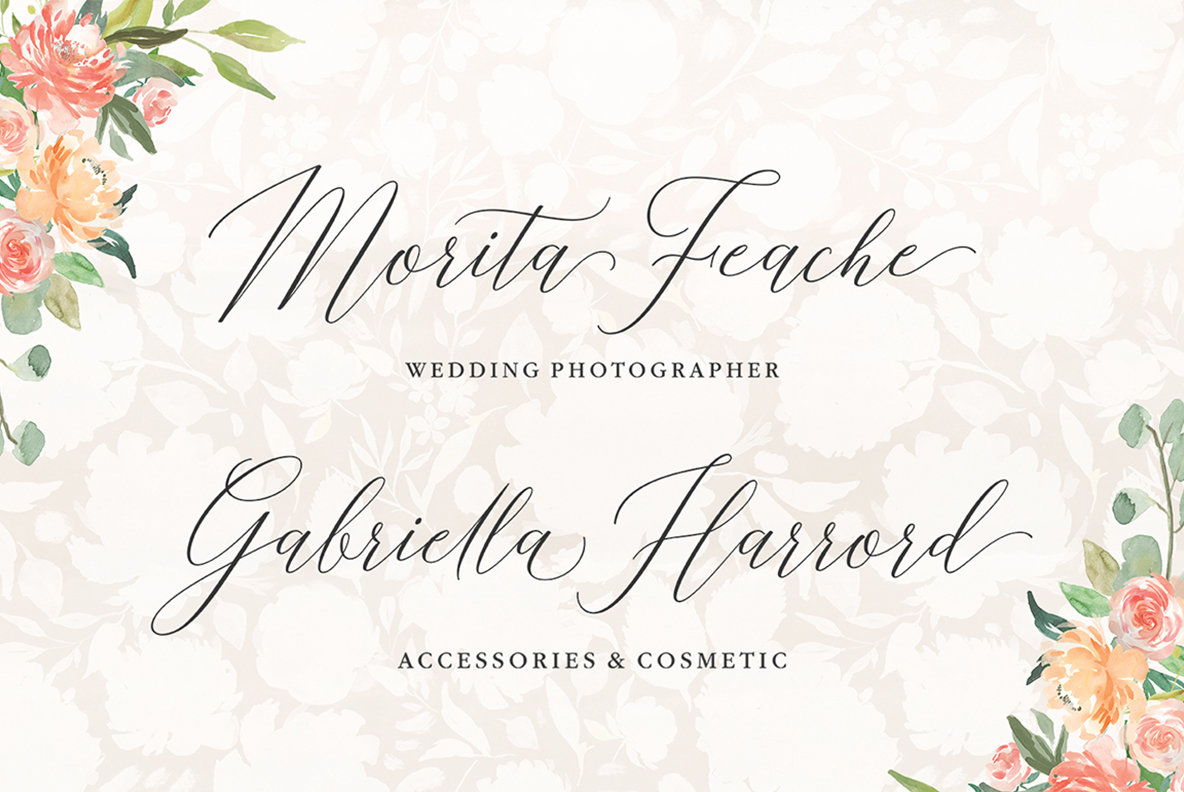
Каллиграфические свадебные логотипы
Лучше всего передать самое сокровенное поможет персональный дизайн ручной работы.
Не случайно кастомная каллиграфия и надписи от руки признаны классикой свадебного дизайна.
Одна из сфер, где каллиграфия работает наиболее хорошо, — различные производства ручной работы, например, создание тортов. Если вы хотите добавить уникальный штрих, подчеркнуть личную преданность или вы владеете бизнесом по производству свадебных продуктов, подумайте об использовании каллиграфии в своем лого.
Создайте свадебный логотип, в который вы влюбитесь
Неважно, планируете ли вы собственную свадьбу или владеете бизнесом, связанным со свадьбами, — правильный логотип может точно передать ваш стиль. Поэтому убедитесь, что вы выбрали именно тот логотип, который лучше всего подходит именно вам. А создать свадебный лендинг, если перед вами стоит такая задача, вам поможет конструктор от LPgenerator.
50 лучших свадебных шрифтов: стиль вашей свадебной открытки 2023
Вы ищете лучшие свадебные шрифты чтобы ваша свадебная открытка выглядела красиво и модно? Мы перечислили лучшие шрифты здесь.
Мы знаем, как пугает задача найти
На свадьбе есть ряд событий и предметов, которые требуют идеального шрифта. Мы понимаем, что вы не можете выбрать какой-либо свадебный шрифт, потому что вы хотите, чтобы этот день стал самым запоминающимся не только для вас, но и для ваших гостей.
- Примечание: строчные и прописные буквы одинаковы. Включает цифры и специальные символы
Шрифт Discover
Семейство шрифтов Westmeath